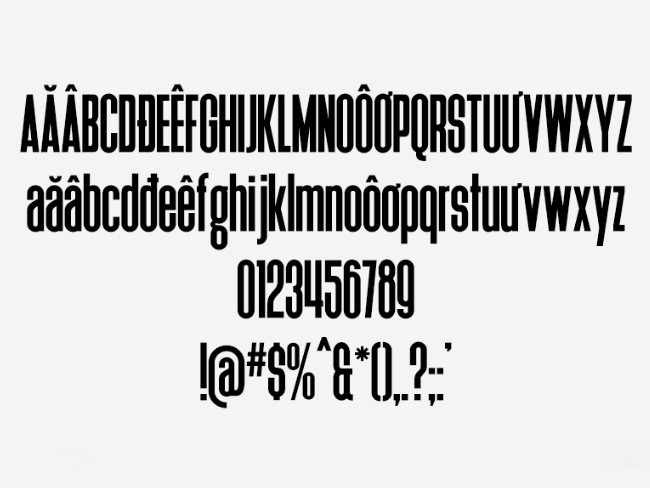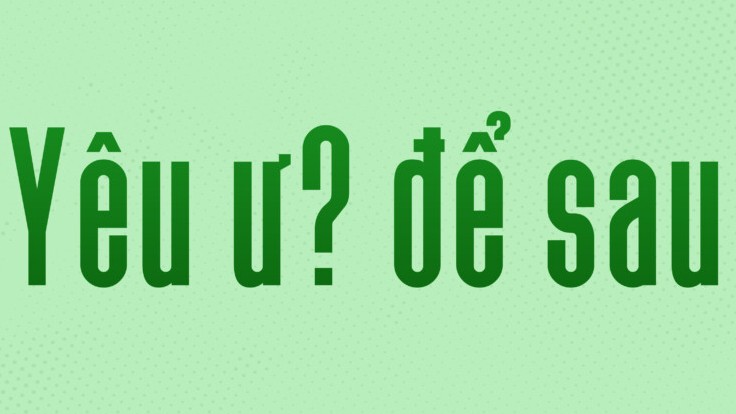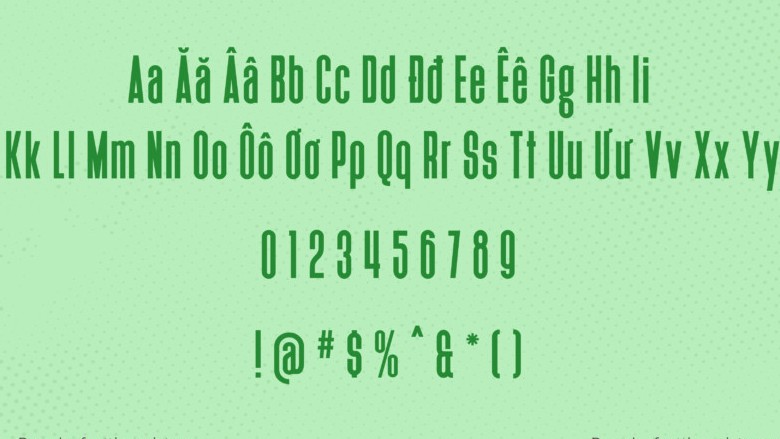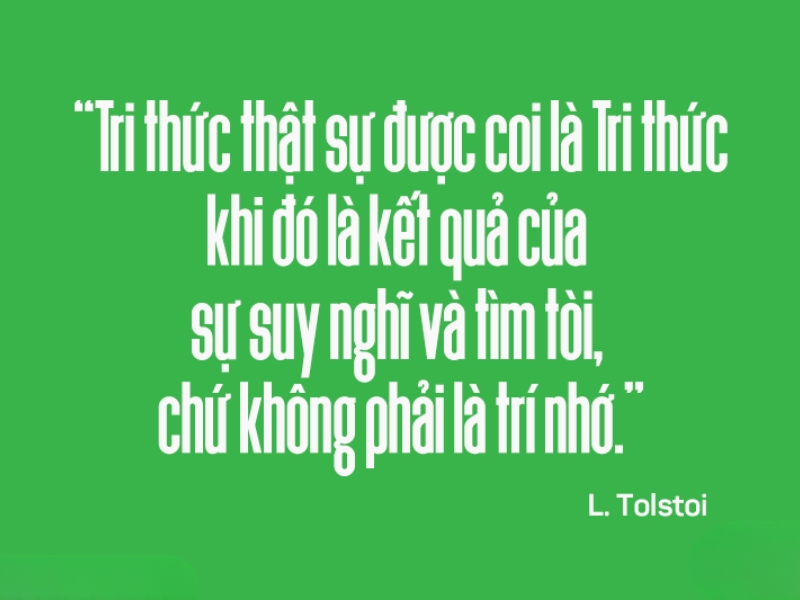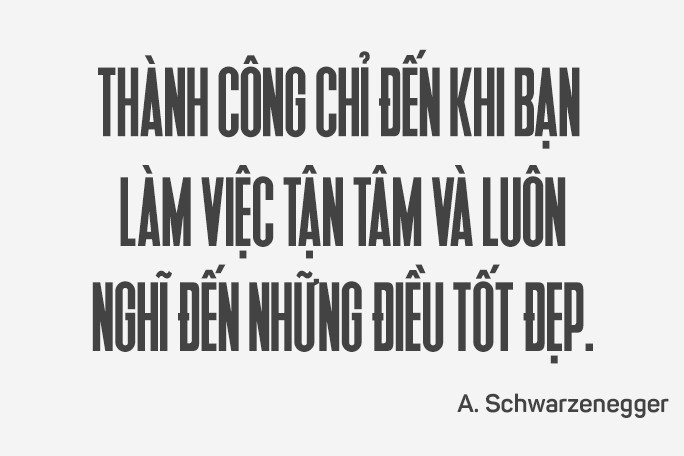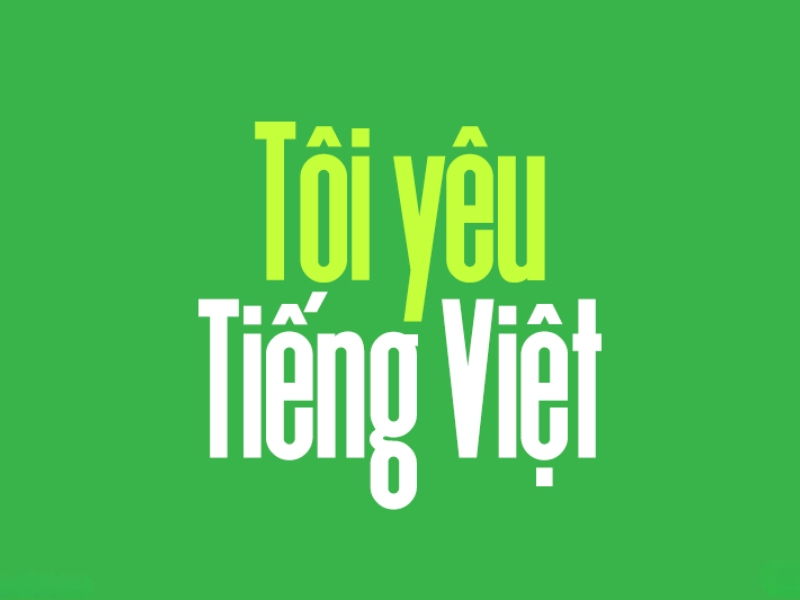
Font Việt hóa SVN Heathergreen là một trong những bộ font Script mang phong cách chữ viết tay được cộng đồng designer yêu thích nhờ những đường nét mềm mại và phóng khoáng. Với ưu điểm đã được tối ưu hóa bảng mã tiếng Việt, bộ font này giúp loại bỏ hoàn toàn tình trạng lỗi dấu thường gặp trên các bản gốc. Đây là lựa chọn lý tưởng cho các dự án thiết kế cần sự thanh lịch, tinh tế và mang tính cá nhân hóa cao.
Đặc điểm nổi bật của font SVN Heathergreen Việt hóa
SVN Heathergreen thuộc dòng font “Signature” với các nét thanh đậm đan xen nhịp nhàng, tạo cảm giác như chữ viết bằng bút mực thực thụ. Điểm khác biệt lớn của phiên bản Việt hóa là sự tinh chỉnh các dấu thanh (huyền, sắc, hỏi, ngã, nặng) sao cho cân đối với cấu trúc chữ, giữ tính thẩm mỹ đồng nhất cho văn bản tiếng Việt.
Bên cạnh đó, font SVN Heathergreen Việt hóa sở hữu hệ thống các ký tự thay thế mượt mà. Khi gõ các cụm từ, các chữ cái sẽ tự động liên kết với nhau bằng những nét uốn lượn tự nhiên, giúp thiết kế của bạn trông chuyên nghiệp và thủ công hơn mà không tốn quá nhiều thời gian chỉnh sửa thủ công.
03 Ứng dụng của font SVN Heathergreen trong thiết kế và đời sống
Nhờ vẻ ngoài sang trọng và tính nghệ thuật cao, SVN Heathergreen được ứng dụng rộng rãi trong nhiều lĩnh vực, từ đồ họa quảng cáo đến thiết kế kiến trúc nội thất:
- Nhận diện thương hiệu Homestay & Cafe: Phù hợp làm logo hoặc bảng hiệu cho các công trình homestay container, nhà lắp ghép mang phong cách vintage hoặc hiện đại nhờ nét chữ phóng khoáng, đầy tính nghệ thuật.
- Thiết kế thiệp và Menu: Mang lại sự trang trọng và cảm giác cá nhân hóa cho thiệp cưới, thực đơn nhà hàng cao cấp hoặc các bao bì sản phẩm thủ công, quà tặng doanh nghiệp.
- Trang trí nội thất: Ứng dụng làm decal dán tường, bảng số phòng hoặc các câu trích dẫn (quotes) trang trí trong không gian sống để tạo điểm nhấn mềm mại cho các mảng tường phẳng trong nhà lắp ghép.
| Tên gốc | Heathergreen Script |
| Phiên bản Việt hóa | SVN (Style No.1 Fonts) |
Gợi ý lựa chọn: Để bản thiết kế không bị rối mắt, bạn nên phối SVN Heathergreen với các font không chân tối giản như Montserrat hoặc Roboto cho phần nội dung chi tiết. Sự kết hợp này giúp cân bằng giữa tính nghệ thuật và sự rõ ràng của thông tin.
03 Lưu ý khi sử dụng Font Script Việt hóa Free trong thiết kế
Dòng font Script thường có cấu trúc phức tạp hơn font chữ tiêu chuẩn, do đó khi sử dụng bạn cần chú ý một số yếu tố kỹ thuật sau:
- Điều chỉnh khoảng cách ký tự: Do dấu tiếng Việt có cấu trúc đặc biệt, đôi khi bạn cần điều chỉnh tay một chút trong AI hoặc Photoshop để các nét chữ không đè lên nhau, đạt tính thẩm mỹ tối đa.
- Tránh dùng cho văn bản dài: Không sử dụng font Heathergreen cho các đoạn văn bản dài, hướng dẫn kỹ thuật hoặc hồ sơ thi công xây dựng vì nét chữ uốn lượn sẽ gây mỏi mắt và khó đọc khi hiển thị ở kích thước nhỏ.